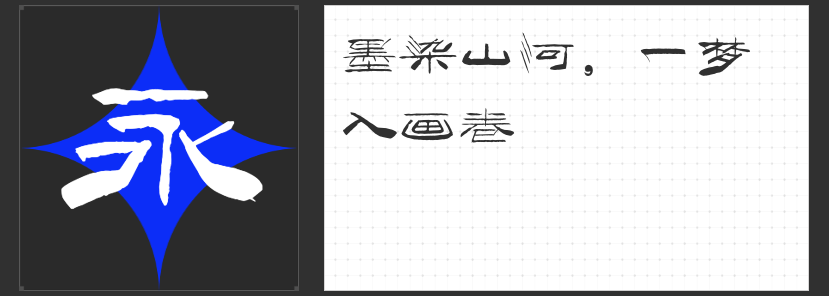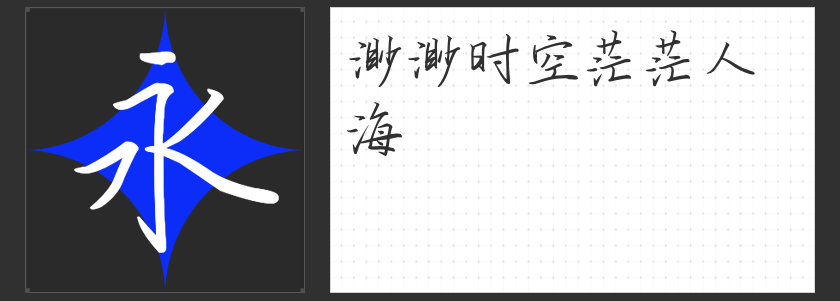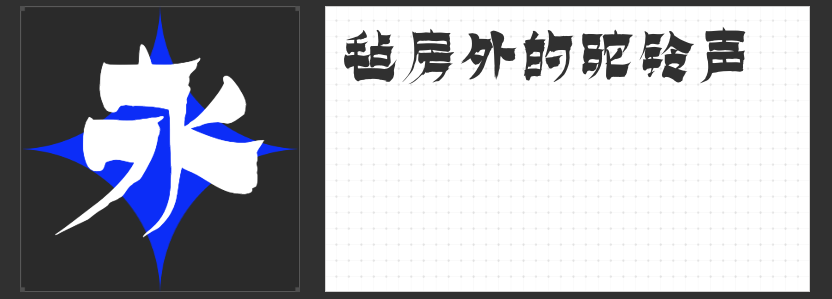
“云书法”系列字体推荐:展现书法艺术的无限魅力
在数字时代,书法字体以其独特的韵味和艺术价值,仍然受到广大设计师和书法爱好者的青睐。今天,向大家推荐四款“云书法”系列字体,它们不仅继承了传统书法的精髓,还融入了现代设计的元素,让书法之美在数字世界中焕发出新的光彩。
第一款是“云书法永刚漆书体”。这款字体笔画厚重,撇字清晰从容,展现出毛笔手书的独特韵味。它的框架醒目,字型端庄,字体风格统一,适用于包装印刷、广告设计、平面设计等多个领域。无论是用于产品包装还是广告招牌,都能吸引人们的目光,传达出品牌的文化底蕴和艺术气息。
第二款是“云书法铁笔隶书体”。这款字体宽扁型的设计,横画长而竖画短,化圆为方,化弧为直,笔画轨迹具有显著的粗细、转承变化。庄重方正、方扁古朴的风格,让人感受到隶书的历史韵味。它适用于需要表现庄重、古朴氛围的设计作品,如历史书籍封面、传统节庆海报等。
第三款是“云书法惠中行书体”。这款行书字体介于楷书和草书之间,字面工整清晰,既有楷书的雍容大气,又兼具草书的灵动活泼。笔画之间连贯流畅、互相映带,用勾、挑、牵丝来加强笔画的联系,展现出行书的独特魅力。它适用于需要表现柔和、舒展氛围的设计作品,如邀请函、画册等。
最后一款是“云书法家韩进水魏碑简繁”。这款字体呈扁方形,撇捺向两侧伸展,收笔前的粗顿以及抬锋,使得整个字形具有厚重感。它在稳健中略显飞扬,规则中正而又富有动态美。适用于需要表现历史感、文化底蕴的设计作品,如碑刻、书法展览海报等。
“云书法”系列字体不仅丰富了数字世界的字体选择,更为设计师们提供了展现书法艺术的广阔舞台。让我们一起感受书法字体的独特魅力吧!